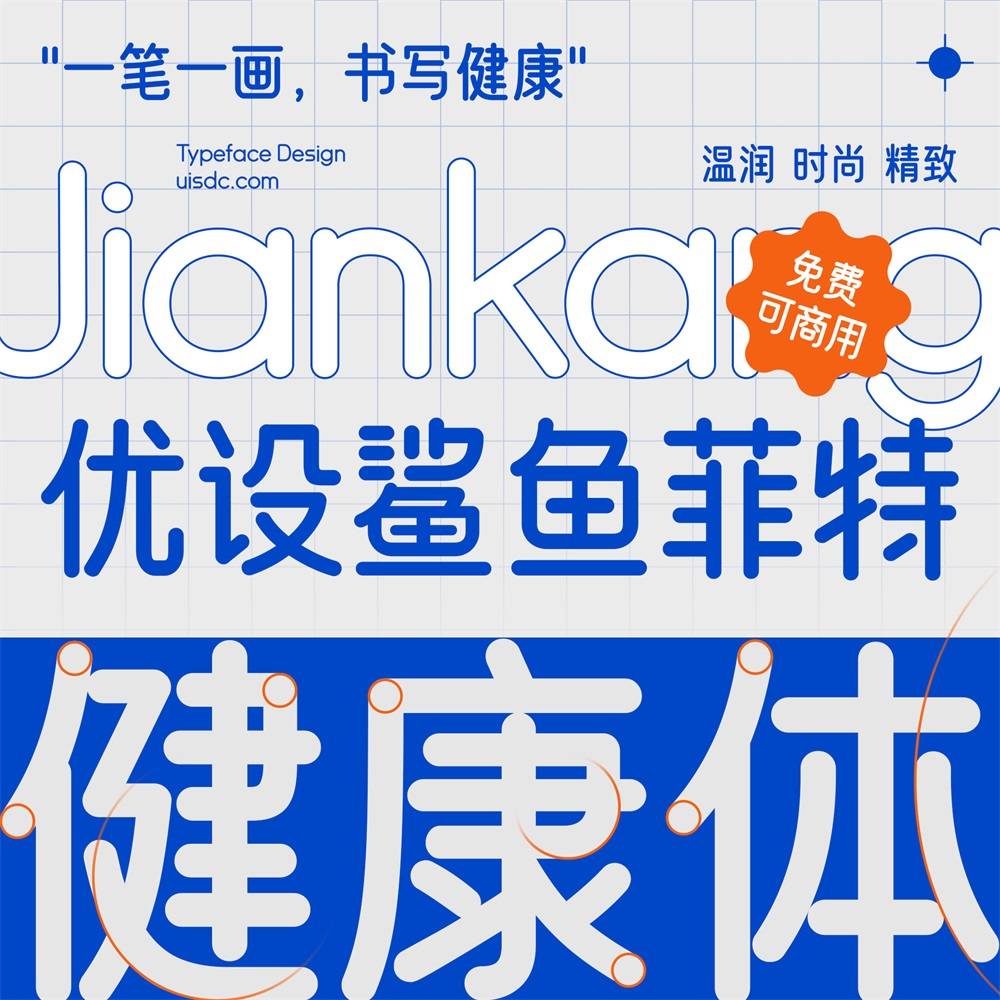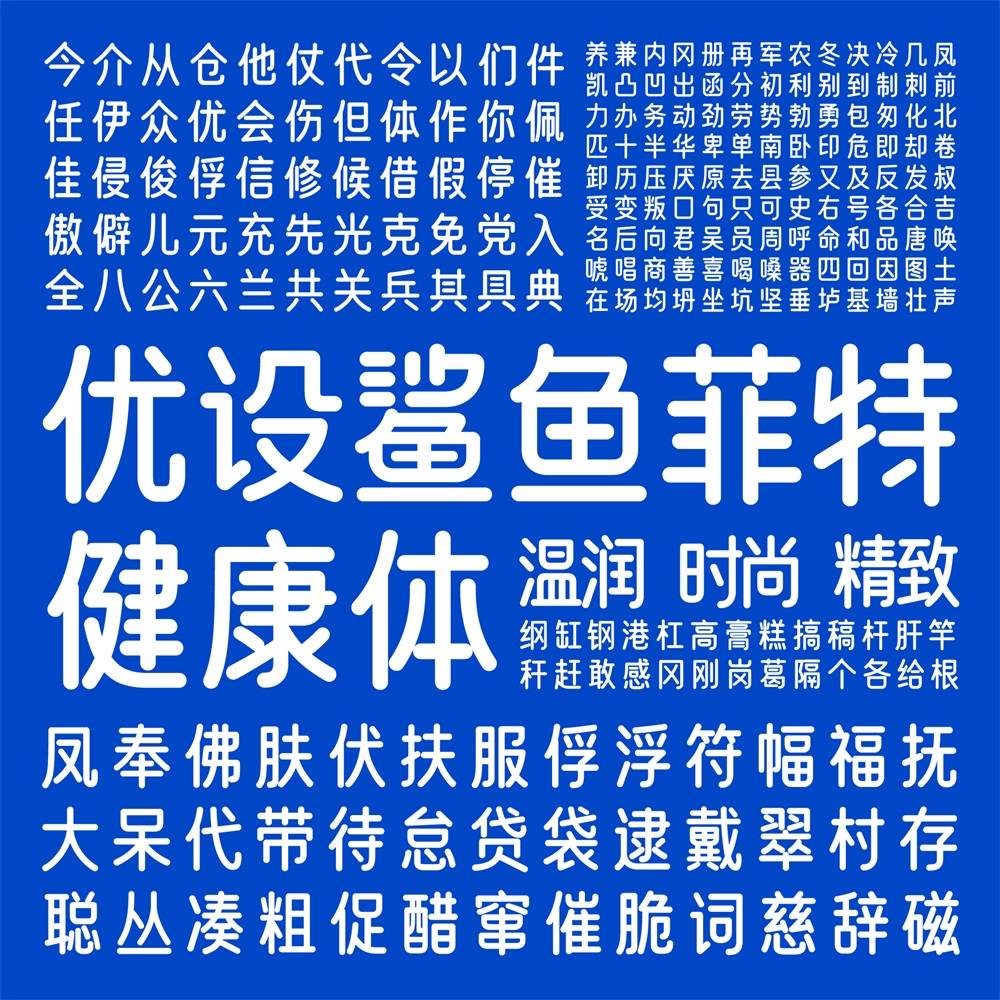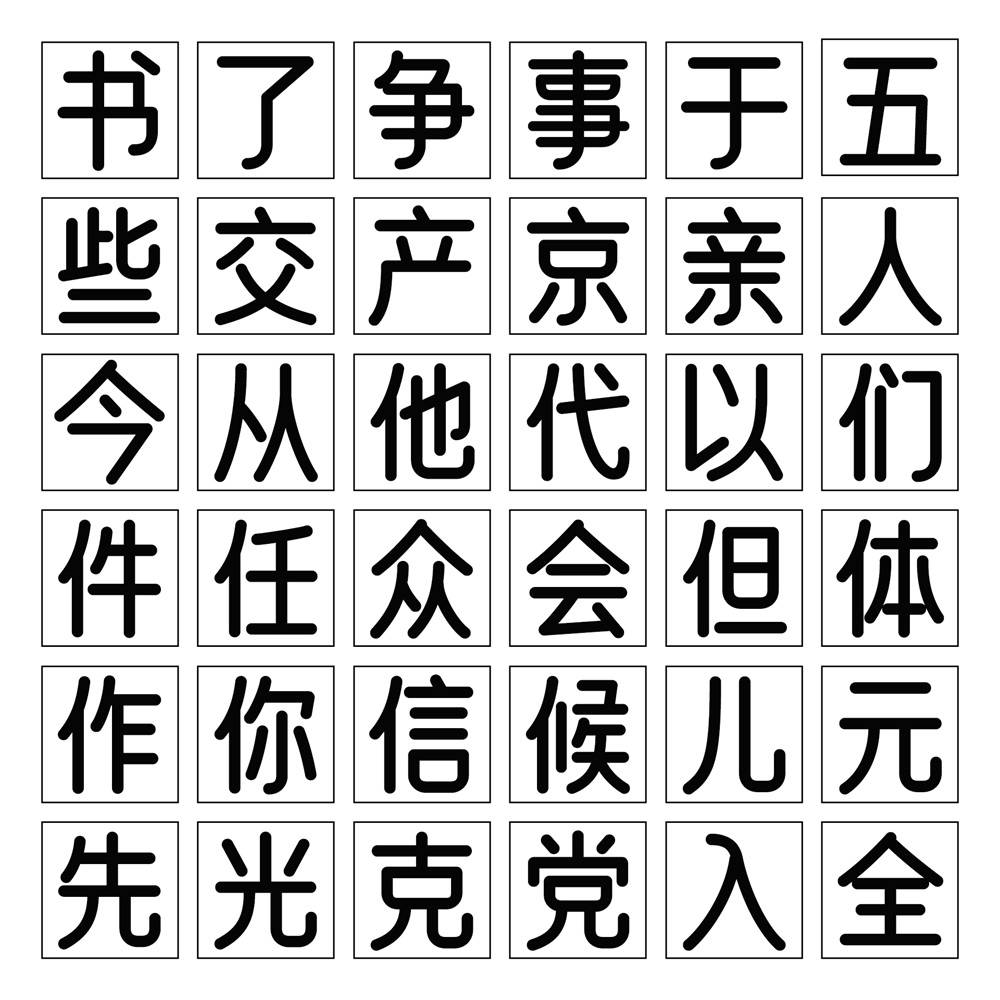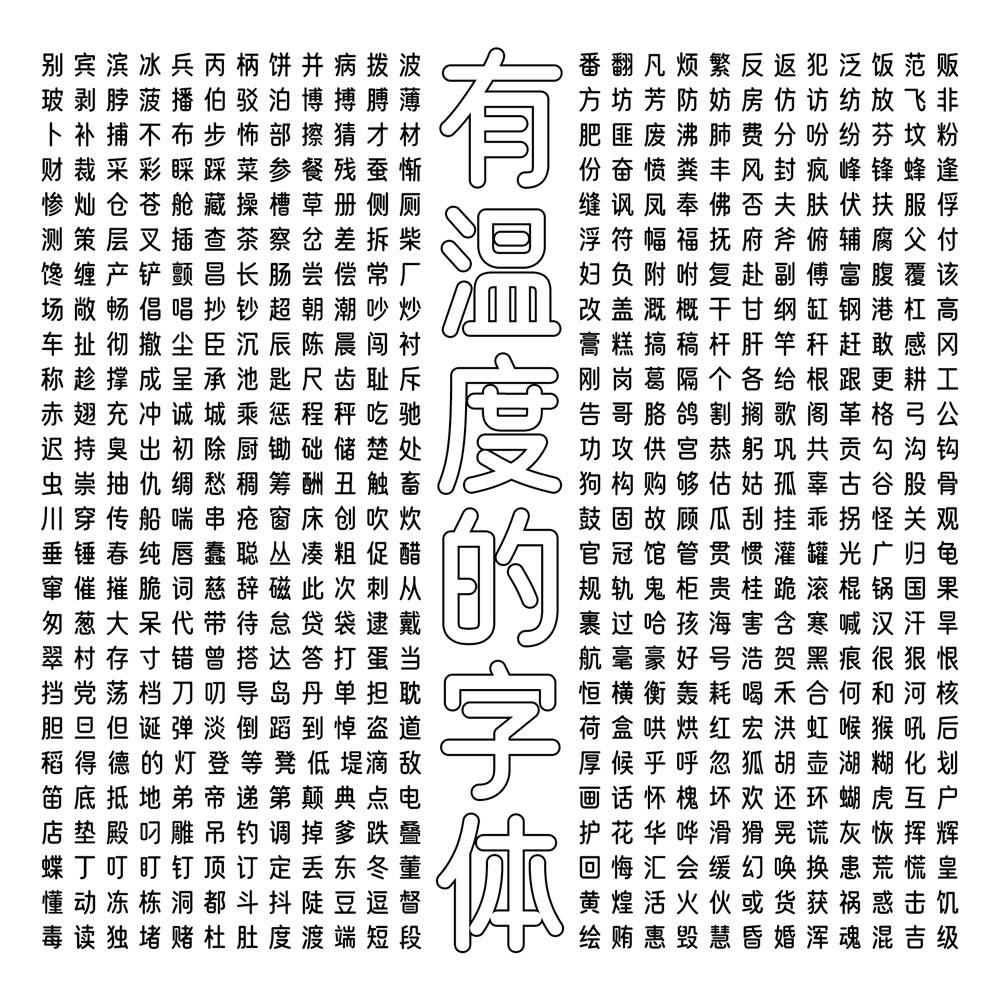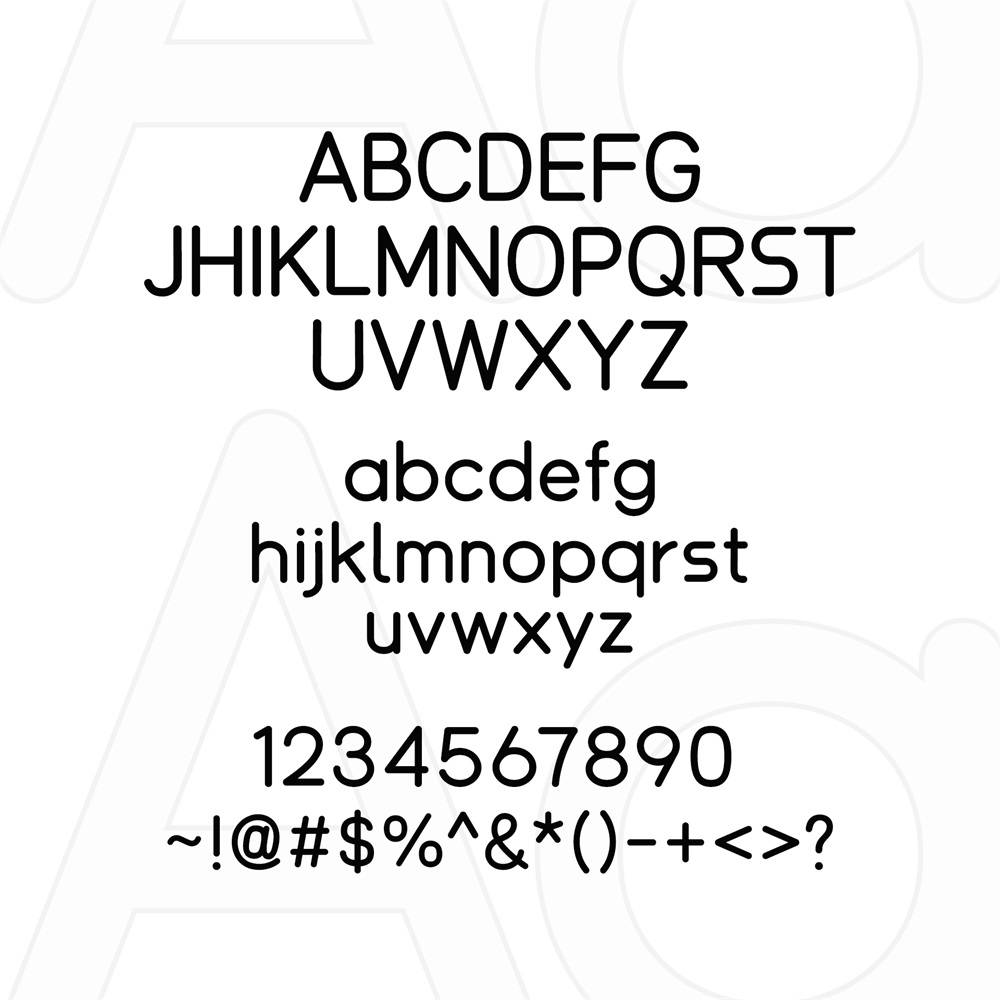
由字绘中国发起,新零售健康轻食品牌鲨鱼菲特联合优设与字由,为广大设计师特推出了一款专为健康而生,电商应用场景极强的优质字体——优设鲨鱼菲特健康体。
在今年即将结束之际,优设及字由共同设计,并联合鲨鱼菲特品牌再次为大家推出的这款鲨鱼菲特健康体,是优设好身体的升级版,造型上要比优设好身体更具有辨识度,设计上更加贴近健康品牌附有的亲和力和现代感,不仅会成为电商设计的又一大助力,更体现了当下追求健康的年轻用户群体特性。
“优设鲨鱼菲特健康体”是一款书写很新颖的字体,字体大方,适合各种设计作品使用!欢迎下载!